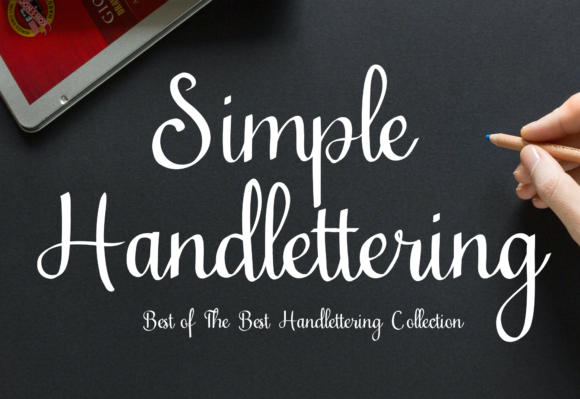
Simple Handlettering
Die richtigen Designelemente zu finden, kann eine Herausforderung sein, aber Simple Handlettering bietet eine außergewöhnliche Sammlung, die Ihre Arbeit sofort aufwertet.
Egal, ob Sie POD-Produkte (Print on Demand), Hochzeitseinladungen oder Social-Media-Grafiken erstellen, Simple Handlettering ist die ideale Wahl.